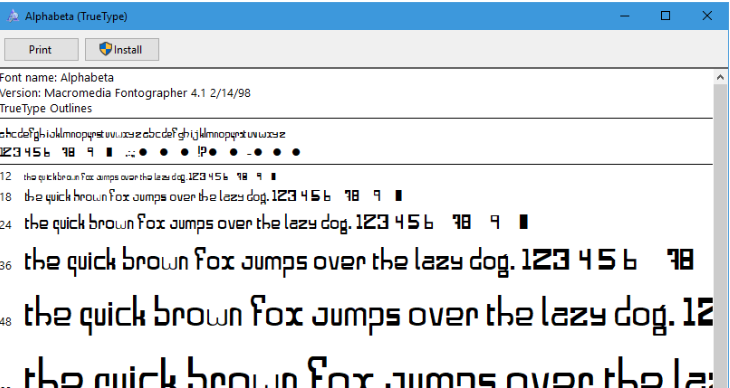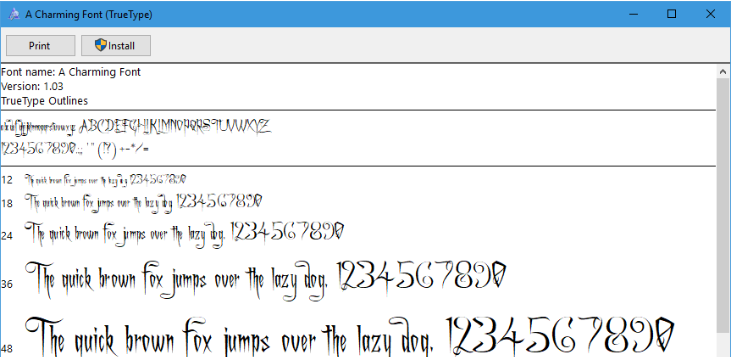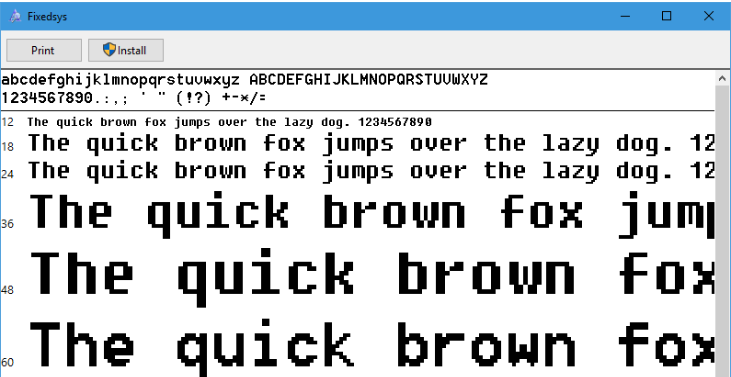
Nếu phải đi tìm phần mềm sử dụng font lạ đẹp mắt nhất có lẽ chúng ta phải trao vương miện cho Auto Cad.  Auto Cad sử dụng các font chữ có dạng .SHX và những bộ font dạng SHX này phù hợp với các bản vẽ hơn các font thông thường bởi nó khá đẹp, gọn nhẹ chính vì thế nó được sử dụng khá phổ biến. Nếu máy tính của bạn không cài bộ font auto cad này thì chắc chắn mở các bản vẽ sử dụng font SHX sẽ bị lỗi. Để tránh các lỗi này các bạn hãy tải bộ Font CAD full bao gồm windows và SHX dành cho phần mềm AutoCad được tip.com.vn tổng hợp ngay dưới đây về máy tính của mình nhé.
Một số hình ảnh về bộ font chữ autocad :